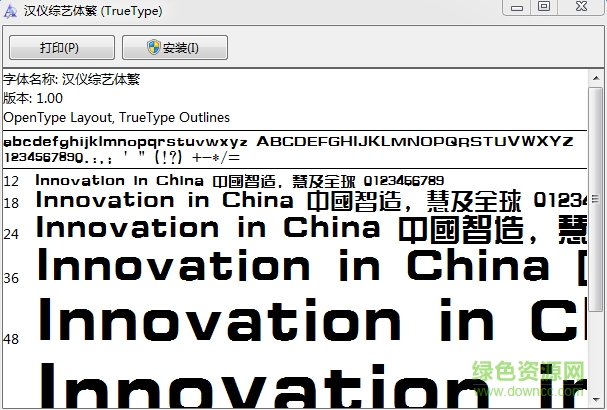
hyk1gf是什么字體?hyk1gf字體是一款漢儀綜藝繁體字體,該字體方正粗大,外形清晰易識(shí),線條變化夸張適度,可用作企業(yè)宣傳字體或海報(bào)字體,需要的朋友趕緊來(lái)資源網(wǎng)在吧!
綜藝體是一種常用的美術(shù)字體,(黑體,宋體,綜藝,楷體等等)。特點(diǎn)是筆劃更粗,盡量將空間充滿。